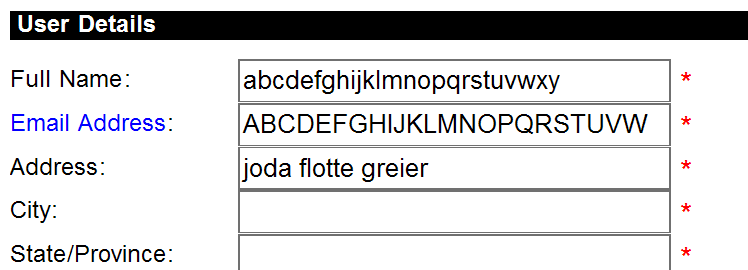
Hvilken font er dette?
Det er ikke verdana. Legg spesielt merke til bokstaven j.
Den som blir brukt i skjemaet har ikke den lille tappen som stikker ut til venstre helt øverst på bokstaven sånn som verdana har.
Det er ikke verdana. Legg spesielt merke til bokstaven j.
Den som blir brukt i skjemaet har ikke den lille tappen som stikker ut til venstre helt øverst på bokstaven sånn som verdana har.
Ok :)
Da vil jeg heller gå for Arial :p
Det kan jeg være enig i :yes: Den likner mer enn Microsoft Sans Serif.